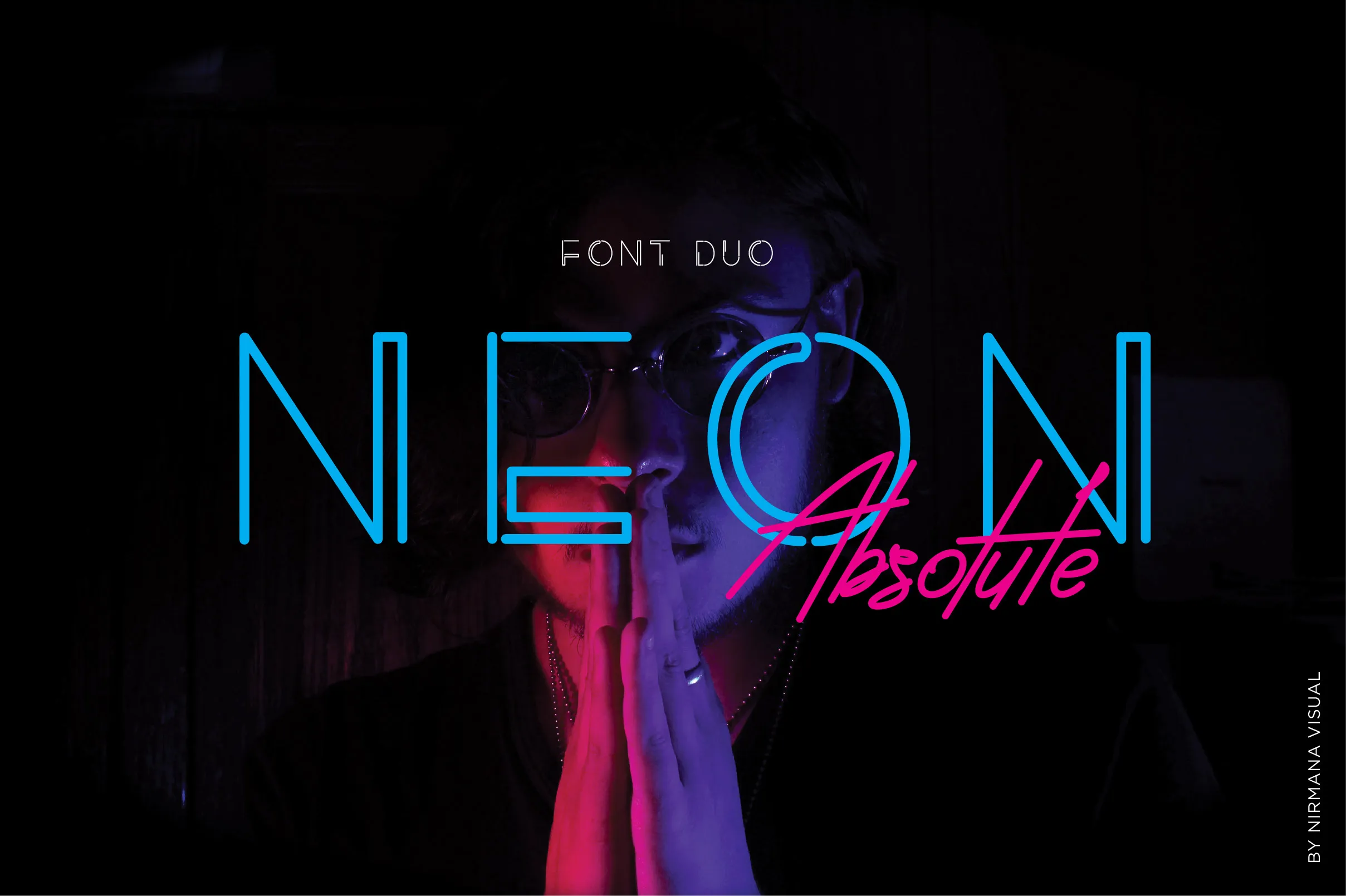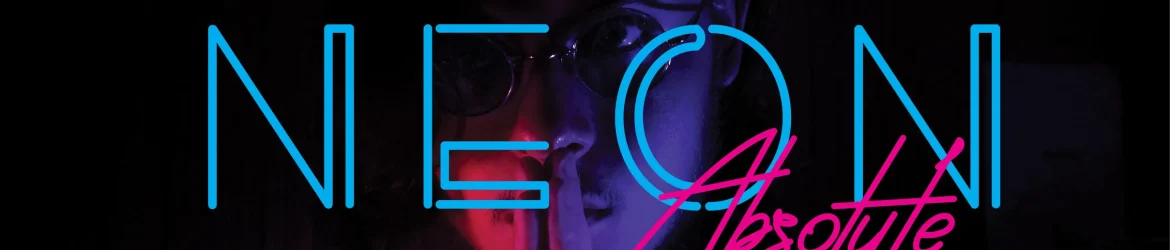
Neon Absolute Typeface – Download Grátis
Introduzimos Neon Absolute, uma elegante e contemporânea dupla de fontes tipo-caligrafia e sans-serif inspirada nas luzes neon dos anos 80. Este sistema de fontes oferece um equilíbrio tipográfico perfeito para uma ampla variedade de projetos de design, desde logotipos e identidades de marca até publicações no Facebook e designs para produtos. Neon Absolute é a escolha perfeita para quem busca unir elegância e modernidade em seus trabalhos gráficos, transformando simples textos em verdadeiras obras de arte vibrantes e imponentes.